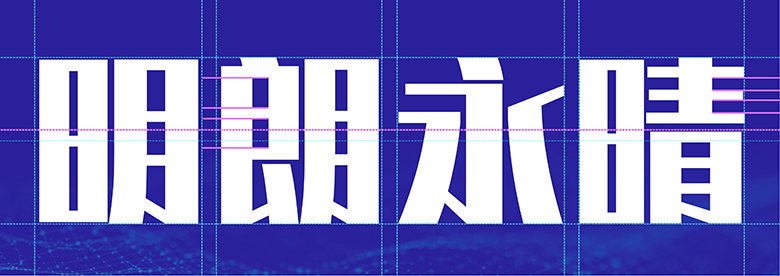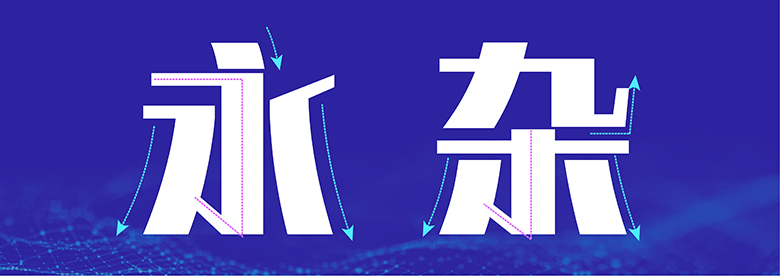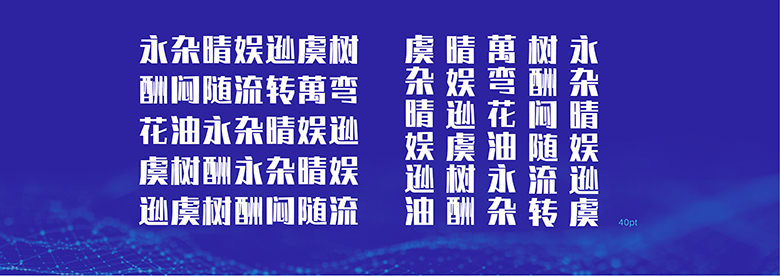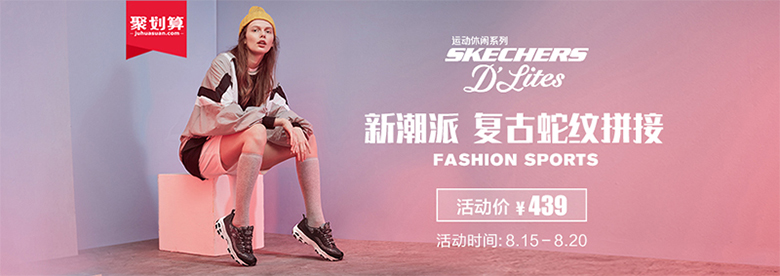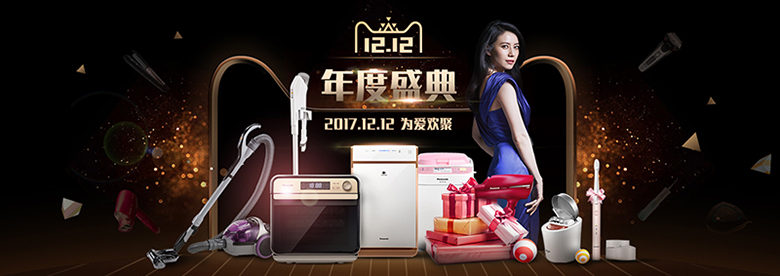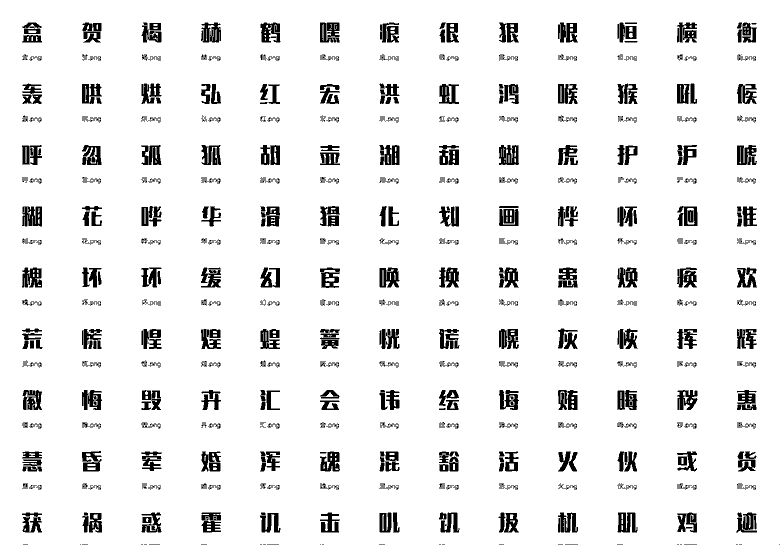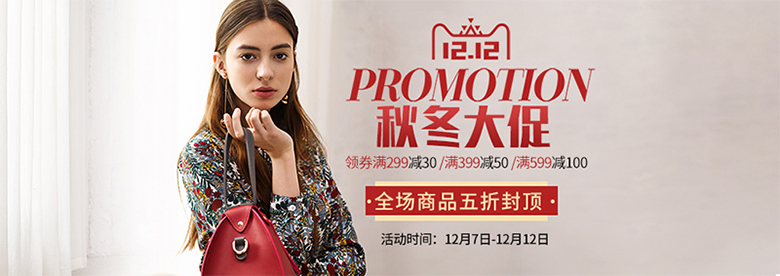
阿里漢儀智能黑體 詳情頁
阿里漢儀智能黑體
今天,人工智能將字體帶入了一個新的世界!
漢儀字庫聯(lián)手阿里巴巴
打造的第一款A(yù)I字體產(chǎn)品
阿里漢儀智能黑體Beta
正式上線!
科技,讓設(shè)計回歸創(chuàng)意
人工智能持續(xù)升溫,
我們能為行業(yè)做哪些貢獻呢?
人工智能踏足字體設(shè)計領(lǐng)域,將幫助設(shè)計師解決大量重復(fù)性工作的問題,提升效率,讓設(shè)計回歸創(chuàng)意,創(chuàng)造出更多的社會價值。
這套字體的beta版本已正式上線并提供給阿里巴巴平臺用戶使用,最終字符集為6763,將在2018年4月份正式發(fā)布。
阿里漢儀智能黑體
字形主創(chuàng)設(shè)計師
中文 | 黃珍元    西文 | 黃永輝
人工智能字庫生成
人工智能技術(shù)專家 | 森飔
參與訓(xùn)機設(shè)計師
盧鑫亞  李曉靜 趙鈺 奚望 胡萌 羅夢怡 滕侍茜 張小玉 譚曉 孔千燁 韓公正
漢儀字庫技術(shù)支持
靳俊
字符集信息
包含GB2312-80標(biāo)準(zhǔn)中3500個常用中西文字符
(Beta版)
符合GB2312-80標(biāo)準(zhǔn)的6763個中西文字符
(正式版)
阿里漢儀智能黑體,字形由漢儀字庫的字體設(shè)計師黃珍元主創(chuàng)設(shè)計,字庫產(chǎn)品協(xié)同阿里人機自然交互實驗室,通過
強大的計算能力自學(xué)生成。這款字體是基于阿里巴巴電商平臺應(yīng)用場景下產(chǎn)生的新分類字體 —— 電商字體。
作為漢儀字庫與阿里合作的第一款電商字體的代表,智能黑體具有強烈的對話性特征。智能黑體基于黑體的橫豎基本特征,加大
橫豎粗細比例,字面飽滿填充整個內(nèi)框,讓字體更加醒目,視覺沖擊力極強,能夠很好的與用戶對話,非常適用于電商類廣告設(shè)計。
電商字體通用性極強,適用于絕大多數(shù)品類的商品。智能黑體區(qū)別于常規(guī)黑體,剛中帶柔,筆畫的走勢上融入了手寫的方式,整體
方正但又不失趣味,度量把握適中。
電商字體的使用受限于自身的傳達介質(zhì) —— 屏幕顯示,字體使用大小也受限于廣告設(shè)計的尺寸,因此這類字體的生成
有別于傳統(tǒng)字庫的精細程度,力求既滿足電商設(shè)計的辨識度及美觀程度,同時又能保證人機協(xié)作快速生成字體的效率。
官方通過大量比對網(wǎng)頁廣告中的文字使用情況,目前完成的阿里漢儀智能黑體將適用于完成網(wǎng)頁圖片中128px以下的標(biāo)題字使用。
電商字體還應(yīng)該具備哪些特質(zhì)呢?
電商字體,顧名思義是基于電商平臺展示開發(fā)的字體,是服務(wù)于電商平臺場景下的設(shè)計展示所需要的字體,例如廣告banner等。
(阿里漢儀智能黑體使用案例,由寶尊電商設(shè)計提供)
除了具備強烈的對話性通用性之外,電商字體將更加高效的解決電商類平臺的用字需求,
由于其自身獨特的屬性,電商字體的開發(fā)將會瞄準(zhǔn)高頻小字符集的需求。
(阿里漢儀智能黑體使用案例,由寶尊電商設(shè)計提供)
電商字體也不再拘泥于傳統(tǒng)的黑宋仿楷分類模式,讓產(chǎn)品分類更加多樣化標(biāo)簽化(少女字體、兒童字體、運動字體等),阿
里巴巴作為中國最大的電商平臺,擁有非常廣泛的消費品種類,相應(yīng)的也需要多樣化的電商字體來匹配多品類的場景,而這背后所
依托的也正是漢儀字庫強大的專業(yè)字體設(shè)計能力與龐大豐富的產(chǎn)品積累。
人工智能字體到底是如何生成的呢?
阿里漢儀智能黑體由阿里計算平臺事業(yè)部PAI產(chǎn)品線Deep Learning團隊與阿里人機自然交互實驗室以及漢儀字庫設(shè)計師協(xié)作完成。
這款字體的生成是人機協(xié)同工作的成果,機器學(xué)習(xí),人工干預(yù),循環(huán)往復(fù),直到最終生成達標(biāo)字庫的一個過程。
人機協(xié)同的過程中,設(shè)計師的工作是極其重要并且無法替代的,包括前期字形創(chuàng)意提供以及生成過程中對于機器的訓(xùn)練。